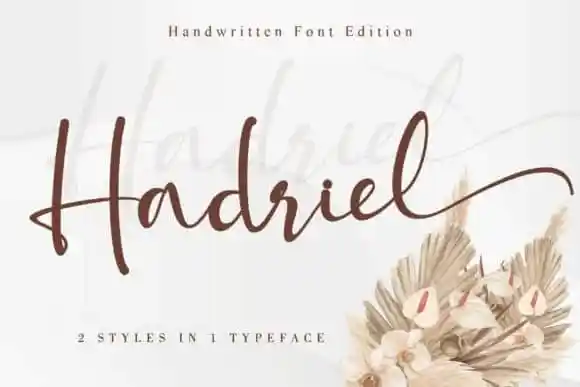
Hadriel Calligraphy Font – Download Grátis
Hadriel Calligraphy Font é uma deliciosa e bela tipografia script projetada a mão por artistas aficionados. Seu design manual reflete paixão e cuidado, evidenciando uma variedade de linhas fundamentais, linhas suaves e traços gráficos encantadores que transformam qualquer projeto em um verdadeiro artigo de arte. Além disso, seu PUA (Portable User Access) permite que você acceda facilmente a todos os símbolos e desenhos alternativos que ele oferece. A fonte tem uma linha fundamental variável e traços gráficos exuberantes e alternativas impactantes, garantindo um resultado visual único e incrivelmente profissional para qualquer projeto de design.